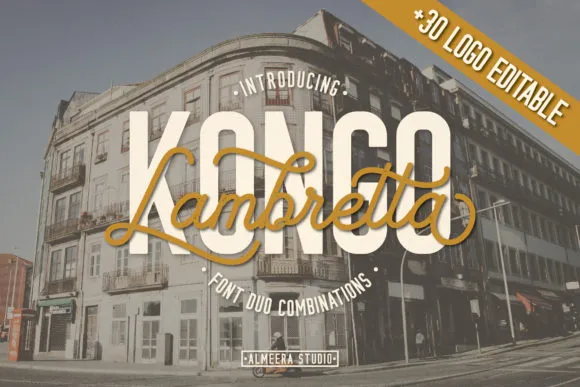
Lambretta Kongo Font Duo – Fonte Grátis
Lambretta Kongo Font Duo
A Lambretta Kongo Font Duo é uma excelente escolha para quem busca uma combinação única de elegância e modernidade. Este par de fontes inclui uma tipografia script e outra de estilo sans-serif, ambas disponíveis tanto no formato regular quanto com versões embutidas. O design original deste conjunto é tão gratificante quanto alegre, destacando-se pela sua beleza arquitetônica que vai além do simples grafiato. A Lambretta Kongo Typeface combina precisão e delicadeza, proporcionando um toque distintivo tanto em aplicativos de mídia social quanto em publicações de design. Se combinadas ou usadas sozinhas, a Lambretta Kongo Font Duo é uma fonte poderosa para qualquer projeto, desde cartazes até websites elegantes. Engajantes e versáteis, estas fontes são perfeitas tanto para aqueles que buscam um estilo mais tradicional quanto para quem busca algo inovador e moderno no design gráfico. Estas fontes da M.0Type foram projetadas para permitir uma combinação única de estilos distintos, oferecendo um conjunto multifacetado de opções que vão agradar designers de todos os níveis. Se você está procurando por uma paleta de letras que seja tanto criativa quanto funcional, então não pode estar mais do que descobrindo estas maravilhosas fontes da Lambretta Kongo Typeface Duo.